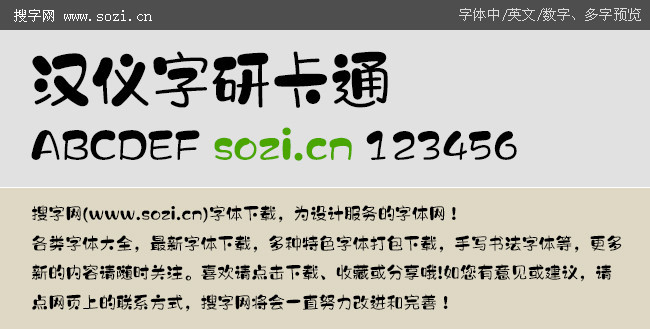
漢儀字研卡通
搜字網(wǎng)給大家提供一款漢儀字研卡通中文字體下載,漢儀字研卡通字體筆觸較為粗實(shí),字體圓潤可愛,適合應(yīng)用于藝術(shù)設(shè)計(jì)、平面宣傳設(shè)計(jì)、網(wǎng)頁設(shè)計(jì)等應(yīng)用。(本字體為個(gè)人非商用版,如需要商用請聯(lián)系漢儀公司購買版權(quán))